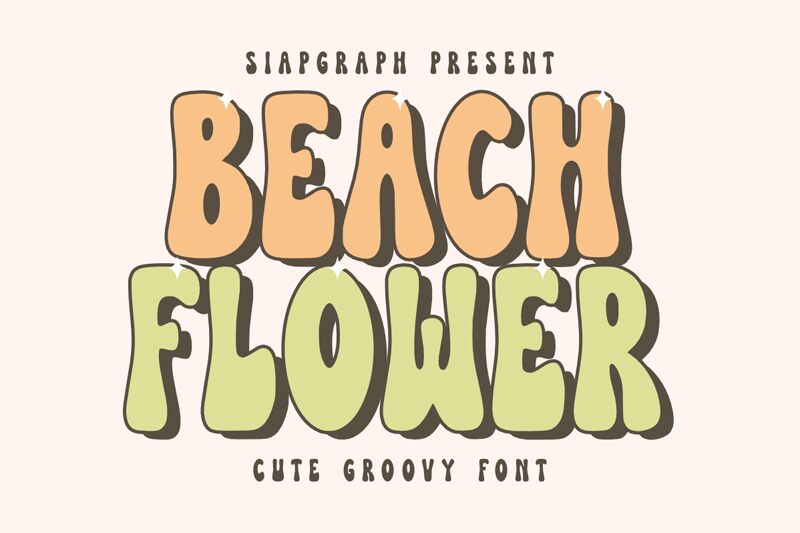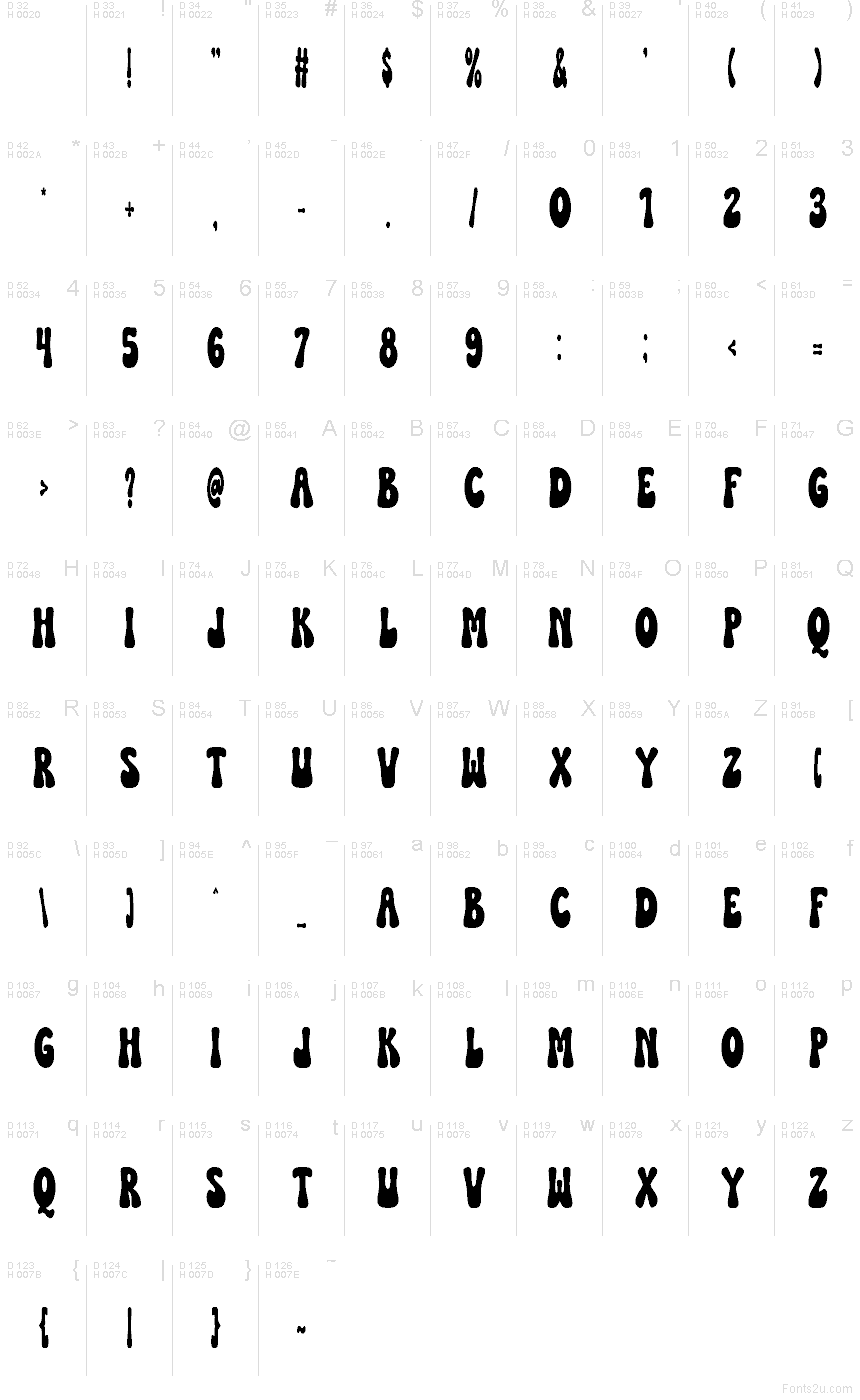
Beach Flower Bold
Beach Flower Bold od SiapGraph Studio je bezplatné groovy písmo, ktoré definujú mäkké, zaoblené tvary pôsobiace hravo a živo, nie stroho alebo tuho. Písmená si udržiavajú plynulý rytmus a evokujú grafický štýl plagátov z konca 60. a 70. rokov bez zbytočnej komplikovanosti.
Vďaka svojim širokým a mäkkým kontúram je Beach Flower Bold prirodzenou voľbou pre letné akcie, branding surfařských obchodov, návrhy nálepiek, obaly albumov alebo výrazné nadpisy na sociálnych sieťach. Skvele sa hodí aj na krátke texty na obaloch či menu v kaviarňach, najmä ak chcete dosiahnuť uvoľnený a radostný vzhľad namiesto neutrálneho titulku.